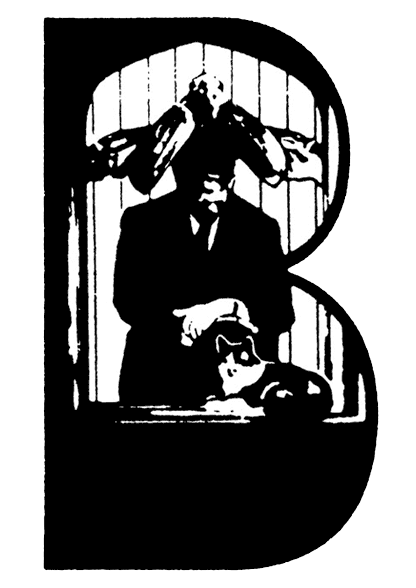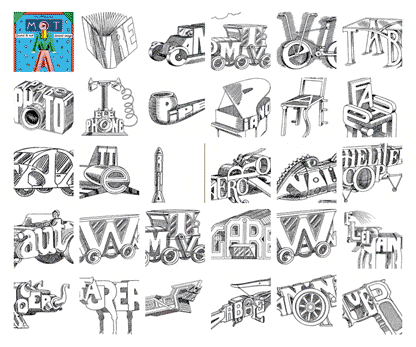
Hommage à l’oeuvre de Jean Alessandrini, écrivain, typographe et illustrateur
Pour l’occasion de cet hommage j’ai logotypé Design et Typo avec le caractère Mirago dessiné par Jean Alessandrini pour l’Atelier Phototypo d’Albert Hollenstein.
Voici quelques mois j’avais écrit un article dans étapes sur la bio et l’œuvre de Jean Alessandrini. C’était autant par honnêteté et passion de critique graphique que par amitié pour Jean qui reste à mon sens un des pionniers du lettrage dans la France d’après-guerre. Me voilà donc transformé en agent d’illustrateur bénévole tant j’aimerais que les éditeurs se souviennent, que les agences de pub redécouvrent le talent de Jean. En hommage à son œuvre j’ai réalisé une galerie la plus complète de ses travaux graphiques.
Les métiers d’Alessandrini?
Fabricant de mots-images n’en n’est pas le moindre, mais ce serait réduire son talent à celui d’un «bricoleur» alors qu’il est à juste titre considéré comme l’un des théoriciens les plus brillants de la typographie (par Maximilien Vox lui-même). Vous pourrez découvrir son essai de classification aux noms aussi évocateurs que poétiques comme *deltapodes*, *filenxtres*, *machinales*, *simplices*, *emparectes*, *claviennes*, *romaines*, *gestuelles*, *germanes*, *hybrides*, *transfuges* et j’en passe… et je suis sûr qu’il serait très heureux à son tour que vous en inventiez de nouvelles. Ses années passées à Pilote et plus tard au contact de Gallimard et Bayard Presse lui ont donné l’occasion de créer une série d’albums-jeunnesse dont le style n’est pas sans rappeler ceux d’un Terry Gilliam ou d’un Georges Lucas dont il est devenu par la suite un des plus grands admirateurs. Mais Jean était un pionnier, et il était sans doute en avance sur son temps. Tout à la main, sans ordinateur, il composait des caractères qui s’arracheraient aujourd’hui s’ils avaient été vectorisés-numérisés. Car c’est bien le seul défaut que je lui connaisse à Jean. Ne pas avoir pris le tournant de l’informatique et laissant à d’autres le soin d’explorer grâce à Fontographer ou FontLab des formes contemporaines dont il avait une vision d’avance.
caractère Mirago dessiné pour l’Atelier Phototypo d’Albert Hollenstein.
Voici quelques temps il a quitté Paris pour s’installer à Strasbourg. La France a beau vivre à l’heure d’internet, n’empêche que les éditeurs sont largement regroupés en Île de France. Autant pour les agences de Pub… et puis c’est vrai aussi que mon ami Jean n’est pas du genre, à décrocher facilement son téléphone, c’est pas qu’il est snob ou orgueilleux, il n’y a pas plus simple et bonhomme que ce garçon éternellement jeune… mais voilà il est affublé d’une timidité maladive et a peur de toujours déranger… sale temps pour les timides ;-) L’Écriture, aussi, parce que Jean a été pris d’une frénésie d’écriture depuis qu’il a remporté un Goncourt Jeunesse, mais le dessin ne l’a jamais quitté, ou peut-être l’inverse ;-)
Cela me remémore mon adolescence typographique. J’ai toujours le petit livret « Le Gymtyp parmi nous » : résumé d’une communication prononcée au Gymnase typographique de la rue Véron par le professeur Jean Alessandrini chargé de cours à l’Institut national de monotypie animal de Draveil (sic)